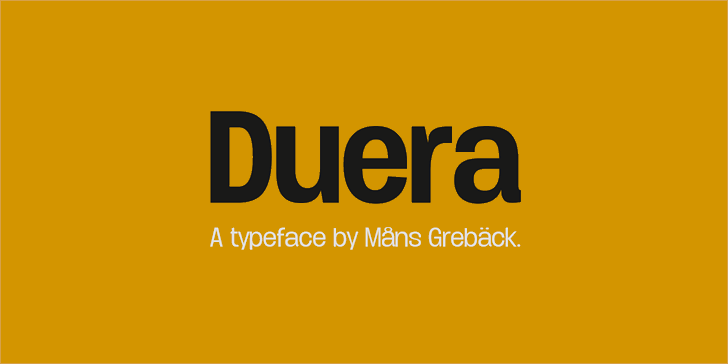
A Duera Font Family é uma elegante família de fontes sans serif criada pelo designer Hamilton. Essa família de 5 fontes inclui diferentes graus e estilos, tornando-a versátil para usar em diversas aplicações, desde logotipos até textos informativos. Com linhas finas e limpas, a Duera promete uma aparência moderna e sofisticada. Ela se destaca por sua facilidade de leitura e seu ar urbano, perfeita para criar um design clean e minimalista. O uso da Duera pode transformar qualquer projeto em algo único e contemporâneo. Para quem deseja incorporar essa bela família de fontes à sua produção, a Mansgreback está disponível com uma licença comercial no site do designer. Não hesite em explorar mais sobre as possibilidades criativas que a Duera pode oferecer para suas necessidades visuais.